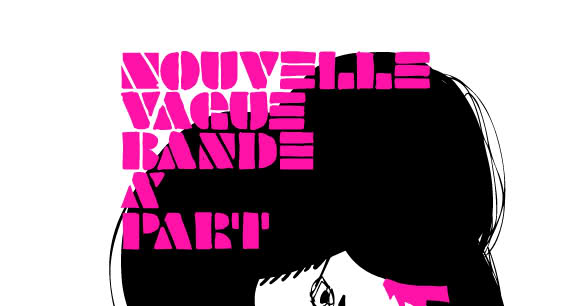
Nouvelle Vague-Schrift
ich bastle gerade an einer Geburtstagskarte eines Nouvelle-Vague-Fans und bin auf der Suche nach der angehängten Schrift (gern auch ähnlich). Blättere nebenbei schon das Fontbook durch, aber vielleicht geht's hier ja schneller :)
sieht handgemacht aus. (vergleiche N und E)
Sieht wirklich so aus ... vielleicht auf dieser hier aufgebaut (hab ich grad im Fontbook gefunden :D )